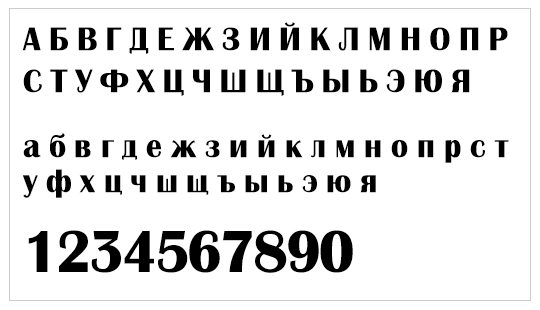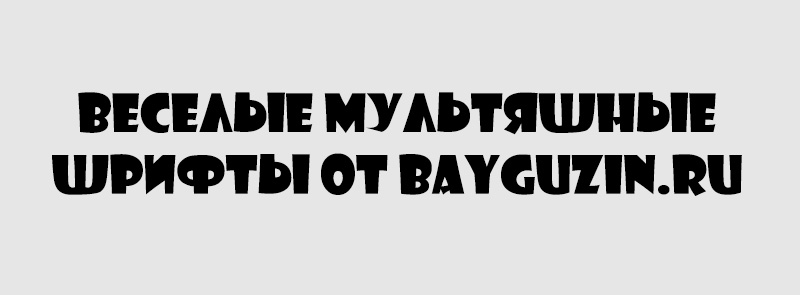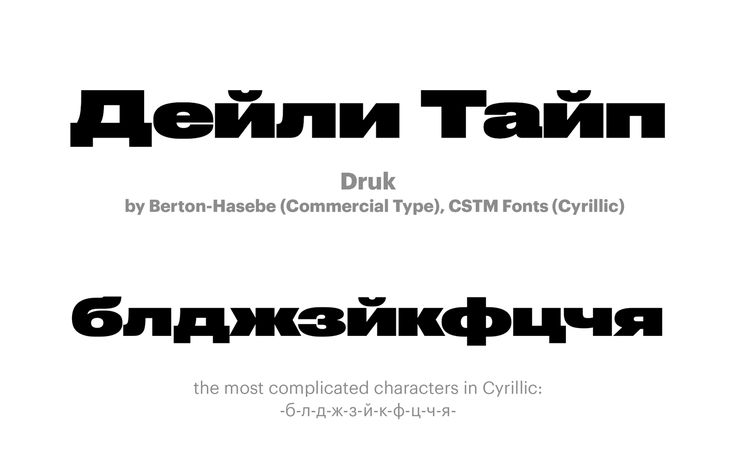
Шрифты кириллица толстые: Жирные шрифты — русские скачать бесплатно
Жирные шрифты | Интернет-креативы
Выбор правильного шрифта для работы в любом дизайн-проекте — непростая задача.. Во многих случаях принятие этого решения занимает гораздо больше времени, чем вы думаете, поскольку из-за большого количества различных шрифтов, которые мы можем найти, это может стать несколько дорогим.
Пользуясь случаем, мы постараемся помочь вам на этих выборах, показываю вам некоторые из лучших совершенных полужирных шрифтов разработать фирменный стиль, плакаты, открытки и т.д. Все они отличаются не только уникальным стилем, но и очень тщательной структурой и дизайном.
толстые шрифты, Именно они привлекают внимание публики.. Они сочетают в себе современность и элегантность в своих планировках, и это то, что мы увидим сегодня. Они очень эффективны, когда дело доходит до передачи сообщения той аудитории, о которой мы говорим, это шрифты, которые будут правильно сопровождать ваши композиции.
Что такое толстый шрифт?
Как мы все знаем из типографики, полужирный, толстый или полужирный, как вы хотели это назвать, Это типографский стиль, который характеризуется тем, что символы, которые он включает, имеют гораздо более толстый штрих. чем вес других типов. Основная задача этого стиля – выделить и подчеркнуть текстовую часть.
Использование толстых шрифтов в мире дизайна претерпело революционные изменения, став незаменимый элемент композиций
. Эта тенденция в графическом дизайне переживает бум в последние годы, и, как многие говорят, размер имеет значение.
С этим типом шрифтов дизайн больше ориентирован на более минималистский стиль, где размеры букв очень большие, чтобы произвести впечатление. Это конструкции, где типографика занимает центральное место в композиции.
Придание индивидуальности текстовой части — основная цель этого тренда на использование крупных и очень толстых шрифтов. Тебе известно, Если вы не хотите, чтобы ваш дизайн остался незамеченным публикой, присоединяйтесь к этому тренду.
Как выбрать правильный шрифт?
хорошая типография, это помогает передать как изображение, так и сообщение, которое мы хотим донести до общественности. о том, кто мы как компания или бренд. В некоторых случаях неудачный выбор типографики может исказить это сообщение и не донести до нашей аудитории.
Чтобы этого не произошло, тогда Мы оставляем вам некоторые основные аспекты для правильного выбора. Подчеркните, что эти советы, которые вы собираетесь прочесть, не являются волшебной формулой и указанную типографику вы найдете сначала.
Первое, что вы должны принять во внимание целевую аудиторию, к которой вы собираетесь обращаться. И типографика, и дизайн в целом должны соответствовать вкусам этой аудитории. Это не то же самое, дизайн, ориентированный на подростков, чем на людей 70 лет.
La выбранный вами шрифт, он должен быть связан с сообщением, которое вы хотите запустить. Для каждого типа сообщения есть подходящая типографика, подумайте, будет ли оно информативным, образовательным, рекламным и т. д.
Еще одним очень важным аспектом является знать, на каких носителях будет воспроизводиться ваш дизайн, если это будет книга, постер, логотип и т.д. Типографика, в зависимости от этого и требуемого стиля, будет более или менее разборчивой. Помимо размышлений о размерах, в которых он будет использоваться.
Один из фундаментальных шагов, который сосредоточится на знании того, чего вы хотите, а чего нет, это поиск ссылок. С помощью этих поисков вы будете сравнивать разные стили в рамках одной классификации.
Благодаря этому вы сможете получить представление о том, что вам нравится, чтобы облегчить окончательный выбор.
Примеры жирных шрифтов
Мы уже рассказывали вам о том, что представляют собой эти типы шрифтов и какова их цель — выделять и привлекать внимание зрителей. Итак, пришло время, вы показали некоторые из лучших примеров этой типографики.
Большой Джон
Доступно для загрузки на веб-портале Behance. Это геометрическая типографика., в котором вы можете найти два разных веса, оба в современном стиле.
Купер Хьюитт
Современный шрифт без засечек, доступный в бесплатной версии для скачивания. Их Персонажи образованы дугами и геометрическими кривыми.
буллат
С ручным стилем рисования, мы предлагаем вам эту забавную толстую типографику. Вы можете использовать его как в титрах, так и в дизайне айдентики, так как он корректно работает в любом проекте.
Будущее Следующее
Он принадлежит к семейству шрифтов Avenir. Эта версия, которую мы представляем вам, идеально подходит для крупных дизайнерских проектов и широкого спектра опор. Он очень хорошо адаптируется к наружной рекламе, социальным сетям, рекламным конструкциям и т. д.